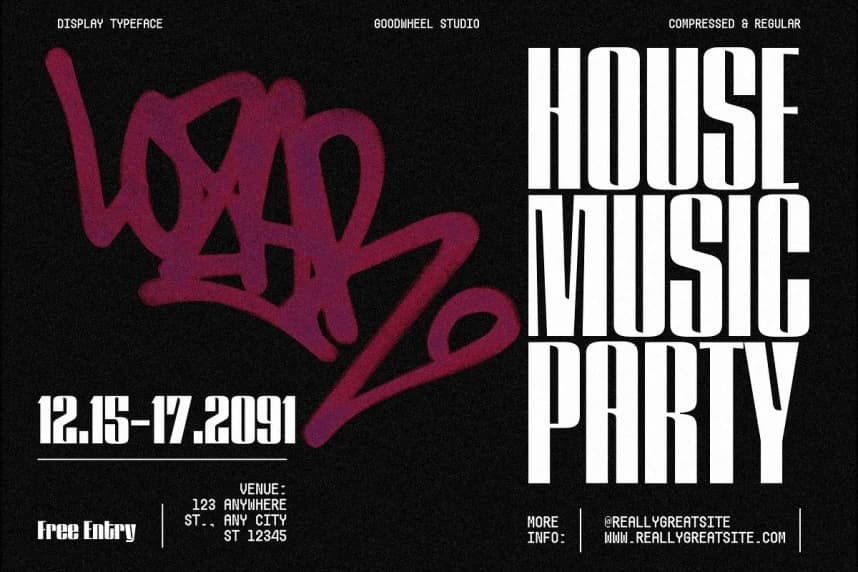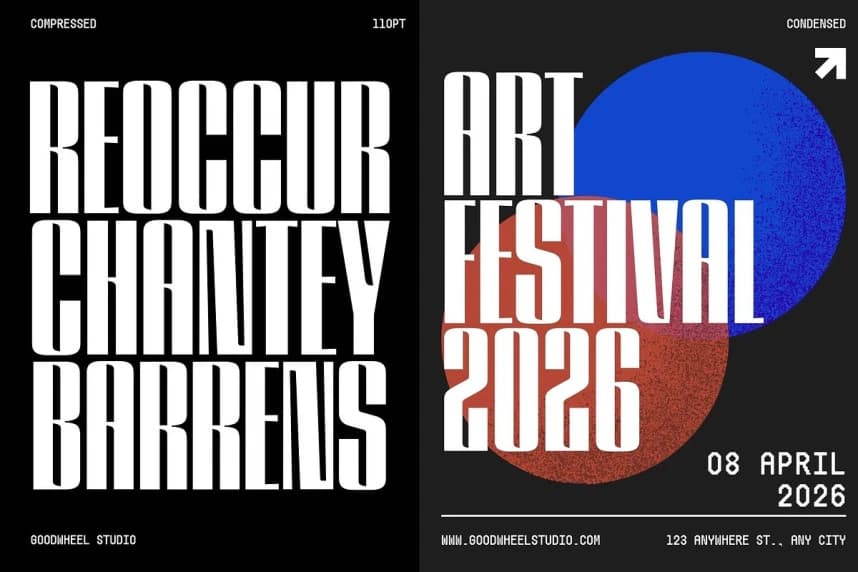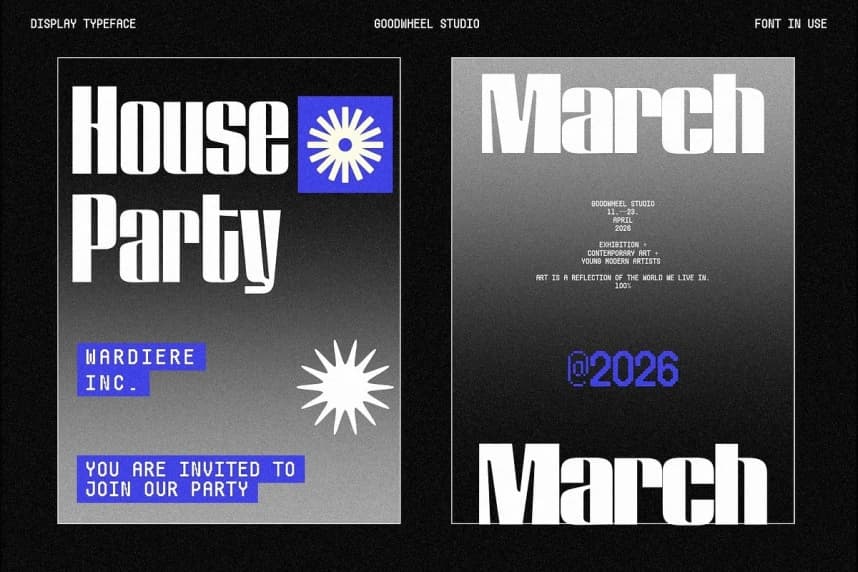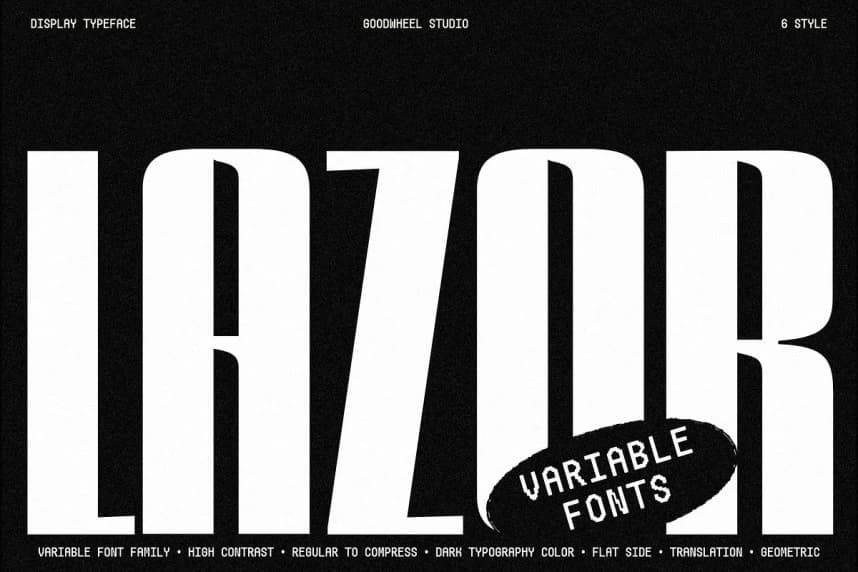
GW Lazor Font Family, modern bir gösterim yazı tipidir; kalın, fütüristik bir karaktere ve keskin geometrik bir yapıya sahiptir. Değişken bir yazı tipi olarak, esnek kalınlık ve stil ayarları sunar; bu da farklı tasarım ihtiyaçları için dinamik tipografi sağlar.
GW Lazor Font Family, cesur ve fütüristik bir karaktere ve keskin geometrik yapıya sahip modern bir gösterim yazı tipidir. Değişken bir yazı tipi olarak, esnek kalınlık ve stil ayarlarına olanak tanır ve farklı tasarım ihtiyaçları için dinamik tipografi sağlar.